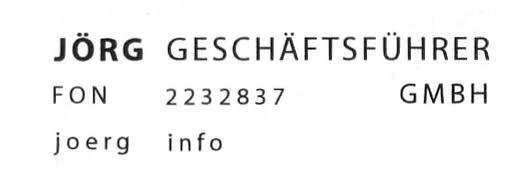
Noch mal: Welche Schrift? Myriad?
Hallo, die sieht mir sher nach Myriad aus, abe rbesonders beim "joerg" unterscheidet sie sich, oder ist das Jörg etwa auch wieder in einer anderen Schrift gesetzt? *confused*
Ich würde schon auf Myriad tippen, und zwar beim «Jörg» auf den Headline-Schnitt. Da sehen die Ö-Pünktchen auch so klein und drangeklebt aus (siehe Anhang)
Könnte hinhauen, oder?
>abe rbesonders beim "joerg" unterscheidet sie sich,
Hehe, ja durch den Einsatz von Minuskeln – im Ernst, hier wurde die Laufweite Myriad extrem erhöht, also die Schrift gesperrt. Das ist alles Myriad.